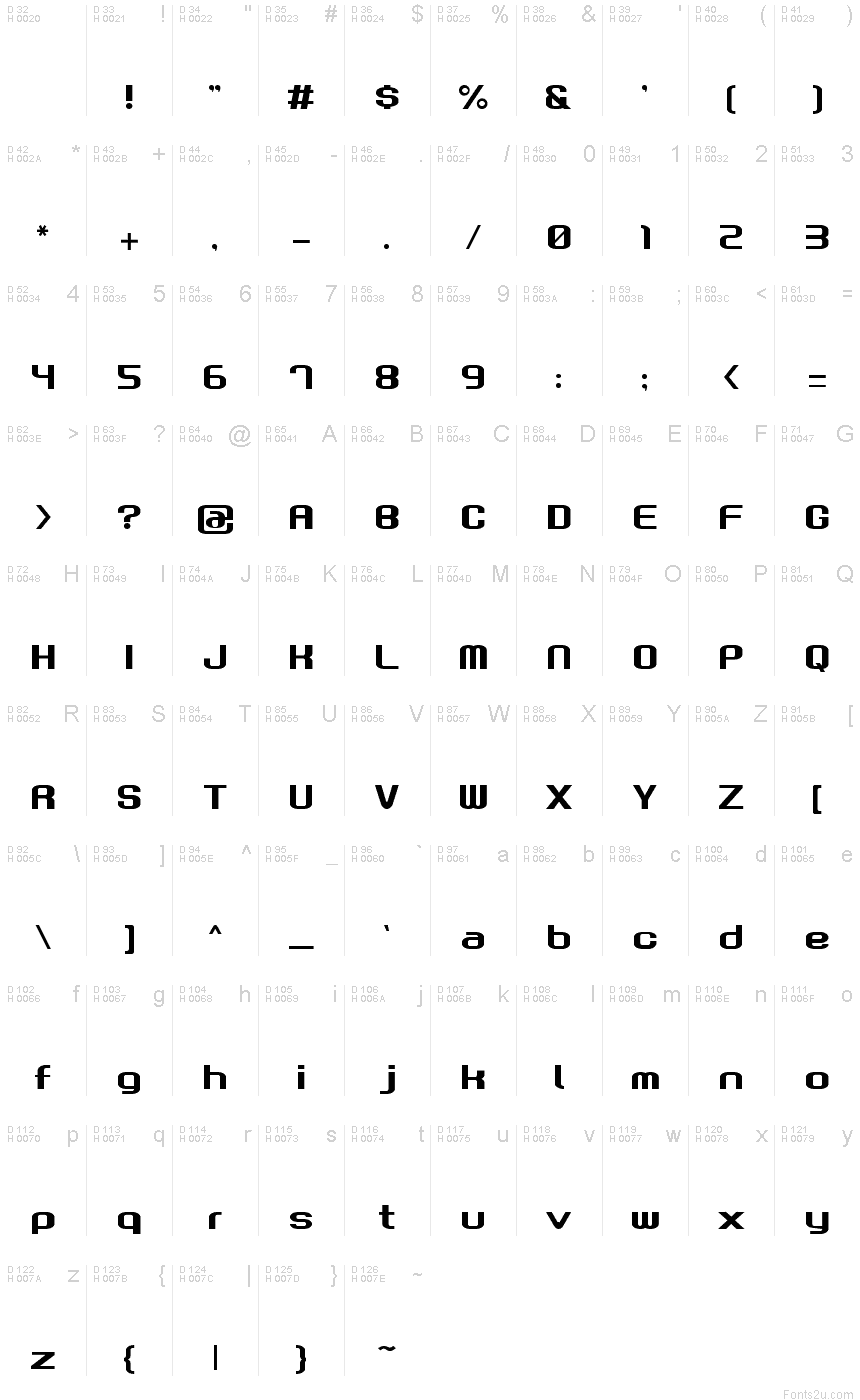
GAU font Root от студии OCY — это бесплатный военный дисплейный шрифт. Толстые, компактные буквы со скругленными углами придают ему вид бронетехники, но плавные линии не дают шрифту выглядеть грубо или старомодно. Ритм плотный и энергичный, поэтому короткие слова складываются в композицию, словно заклепанные металлические пластины.
С GAU font Root жирные заголовки и цифровые коды сразу приобретают тактический, индустриальный и слегка футуристичный вид. Этот бесплатный шрифт отлично смотрится в логотипах игр, эмблемах команд, киберспортивном брендинге, научно-фантастических плакатах, технической упаковке и на вывесках, где нужен мощный визуальный акцент с первого взгляда. В малых кеглях сочетайте его с чистым нейтральным гротеском, чтобы основной текст оставался читабельным.